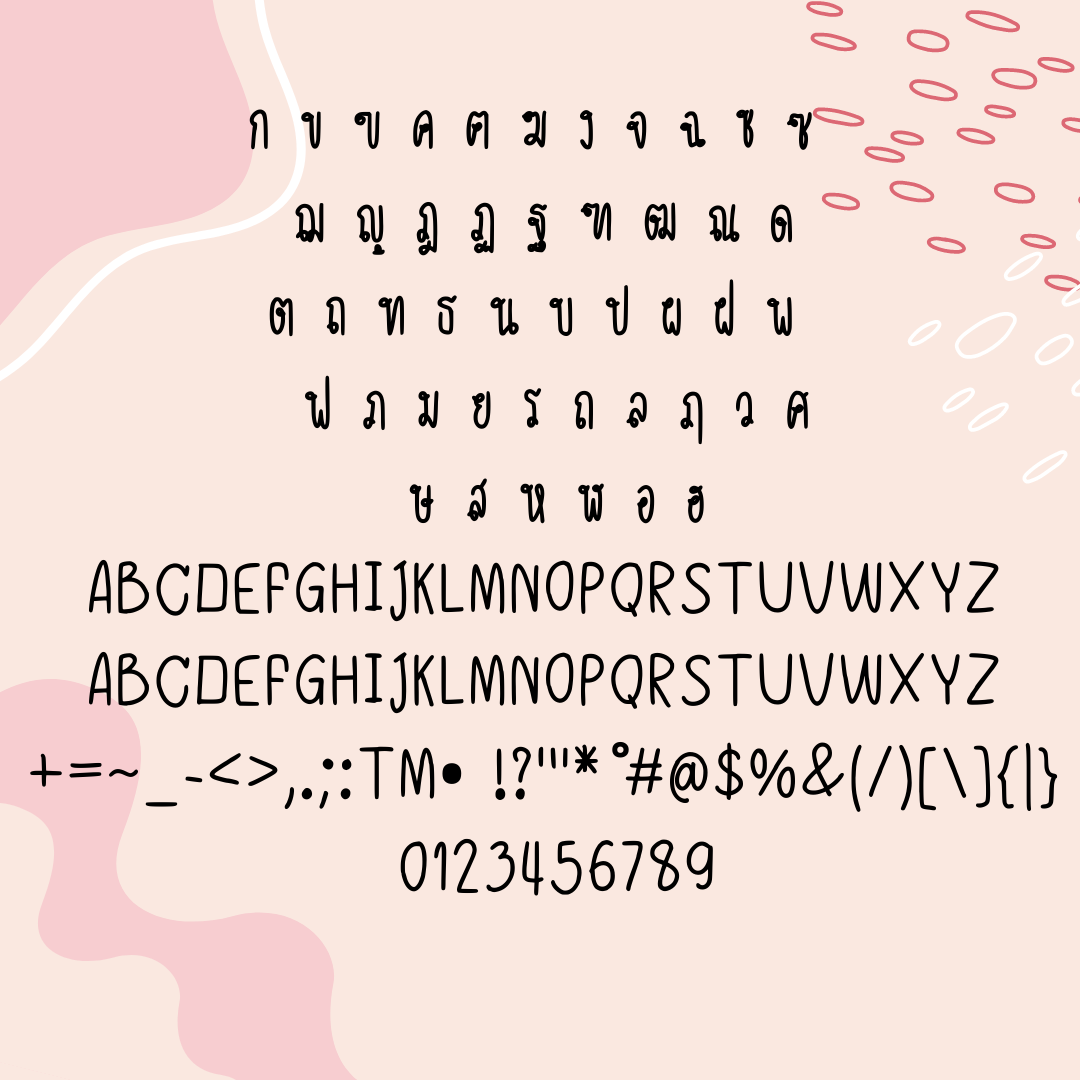
ฟอนต์ ฮันนี่ (Honey)
ฟอนต์ ฮันนี่ (Honey) ฟอนต์ที่มีเอกลักษณ์ ใช้ทำงานสไตล์น่ารักๆ จดโน้ต หรือจะทำแฟลชการ์ดก็ดูดี แจกฟรีไปเลยเวอร์ชันทดลอง : แบบปกติ 1 น้ำหนัก ใช้ได้เฉพาะแบบส่วนตัว เช่น ใช้ในการศึกษา ใช้จด ใช้ตกแต่งสมุดโน้ตตัวเอง